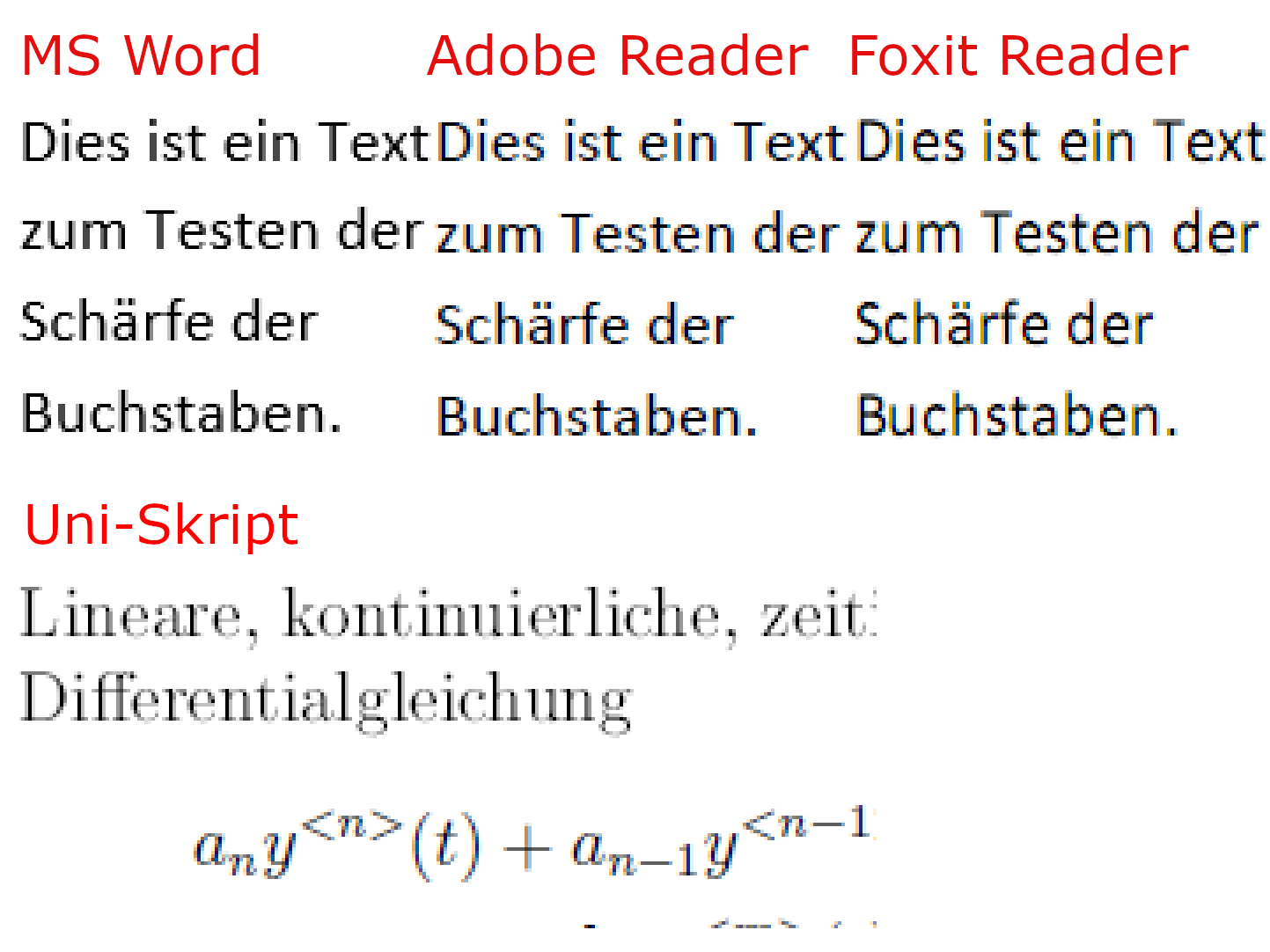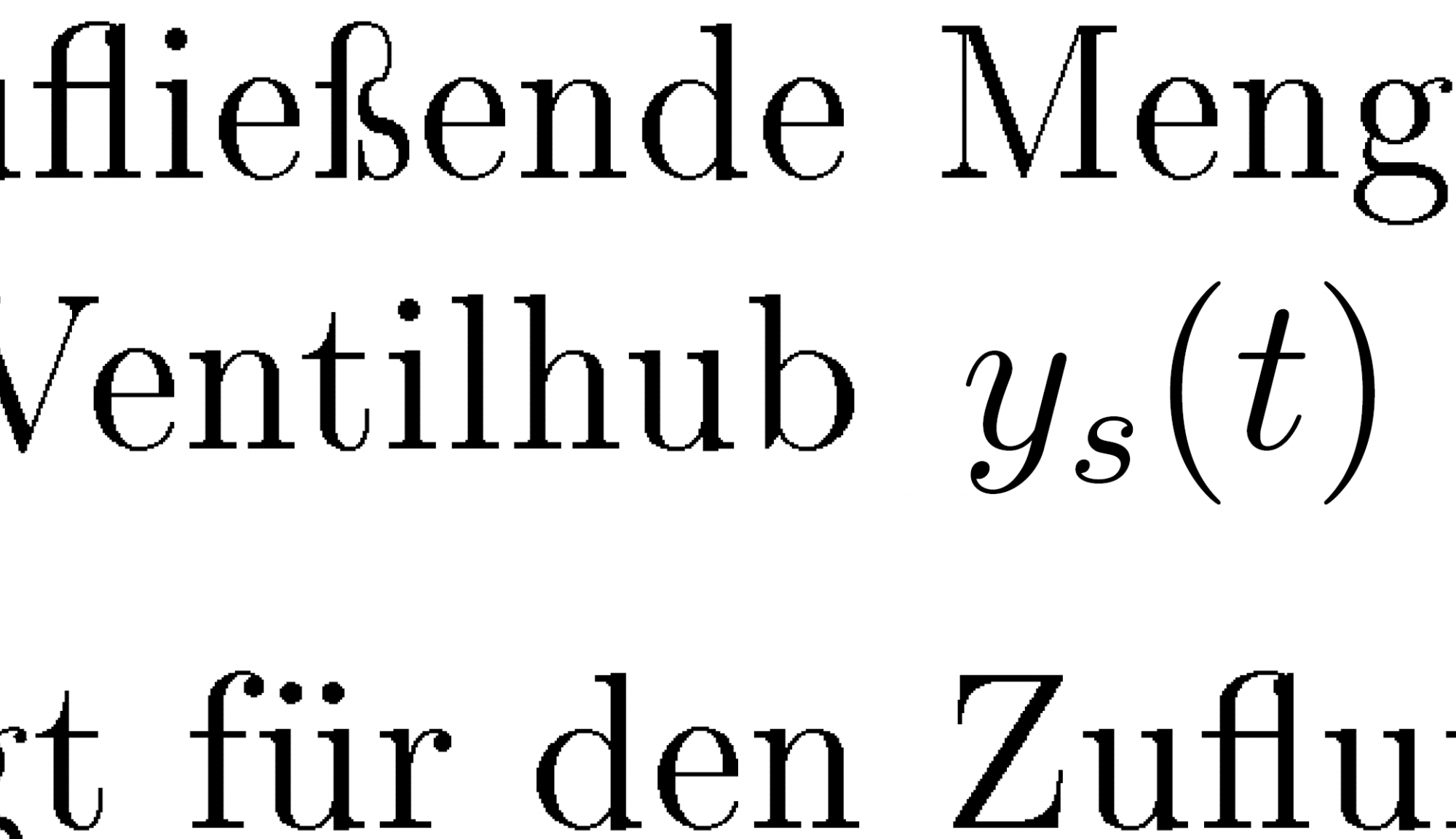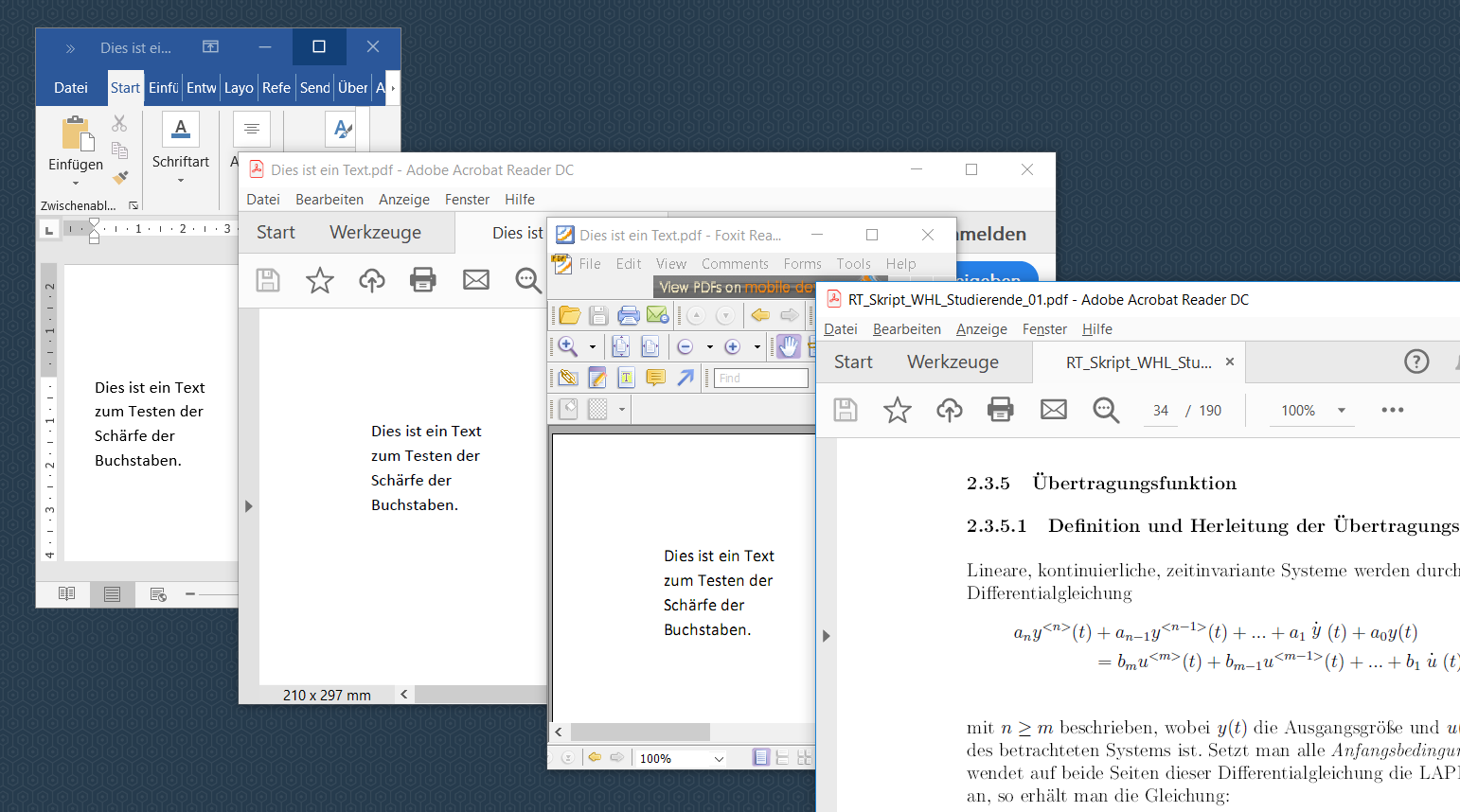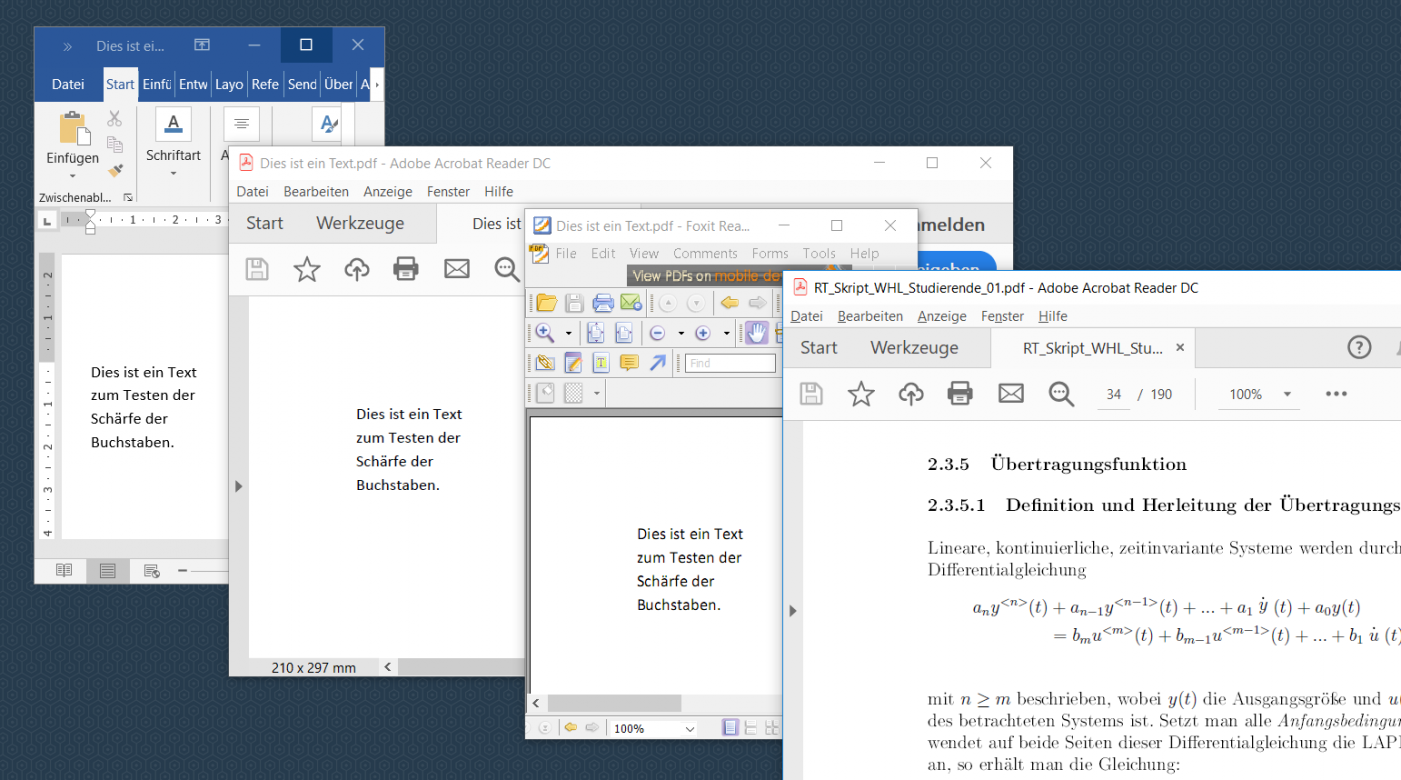
[Mitglied dyse…] Geschrieben Dezember 12, 2019 Teilen Geschrieben Dezember 12, 2019 Moin moin, mir ist das schon öfters aufgefallen. PDFs sehen immer etwas unscharf aus. Woran liegt das? Ich habe mal einen Screenshot gemacht um zu verdeutlichen was ich meine. Das ist nicht nur auf meinem PC so. Besonders fällt es mir bei Uni-Skripten die mit LaTeX geschrieben wurden auf. Vielleicht liegt das an der Schriftart, dass es da stärker ins Gewicht fällt. Bei Word ist der Text deutlich schärfer zu sehen als später in der PDF-Version des selben Dokuments. Das Skript ist nochmal deutlich unschärfer. Ich habe es auch mal vergrößert, damit man es besser sieht. Kann man das ändern? Viele Grüße Daniel Link zu diesem Kommentar
Ralf Herrmann Geschrieben Dezember 12, 2019 Teilen Geschrieben Dezember 12, 2019 Die Buchstaben sind Vektorbeschreibung. Die Umwandlung in die nötige Pixeldarstellung und die dabei angewendete Kantenglättung erfolgt durch eine Render-Engine. Software-Anwendungen können dabei auf das Betriebssystem zugreifen oder eine eigene Render-Engine mitbringen. In der Folge sehen Texte daher in verschiedenen Anwendungen oder auf verschiedenen Betriebssystemen immer etwas anders aus. Direkt eingreifen kann man da selten. (Gegebenenfalls nach Einstellungen zur Kantenglättung suchen.) Es ist auch eine Frage der Gewohnheit und Geschmacksache. Der schärfere Text ist nicht automatisch der bessere. Man kann übrigens ruhig noch näher drangehen. Dann sieht man die Unterschieden in der Kantenglättung noch besser: 2) und 3) verwenden Subpixelkantenglättung. 1) nicht. Bei 2) wird eher in der Horizontalen gearbeitet. Bei 3) auch in der Vertikalen. Kann alles seine Vor- und Nachteile haben. 1 1 Link zu diesem Kommentar
[Mitglied Call…] Geschrieben Dezember 12, 2019 Teilen Geschrieben Dezember 12, 2019 Bei LaTeX kommt es darauf an, welche Schriften eingebunden werden und auf welchem Weg das PDF erzeugt wird. Der alte, steinige Weg lautete: latex erzeugt *.dvi-Datei, dvips erzeugt Postscript-Datei, ps2pdf erzeugt PDF-Datei. Ganz zu Beginn kamen dabei sehr große, unschön aussehende PDFs heraus. Uni-Skripte sehen heute auch noch manchmal so aus. Alternativen zum umständlichen Weg: pdflatex oder xelatex 1 Link zu diesem Kommentar
[Mitglied 6701…] Geschrieben Dezember 12, 2019 Teilen Geschrieben Dezember 12, 2019 Ich würde probieren, ob ClearType daran Schuld ist, das führt ja systembedingt zu unschärferen Abbildungen. Link zu diesem Kommentar
[Mitglied Seba…] Geschrieben Dezember 12, 2019 Teilen Geschrieben Dezember 12, 2019 vor 15 Minuten schrieb bertel: Ich würde probieren, ob ClearType daran Schuld ist, das führt ja systembedingt zu unschärferen Abbildungen. Cleartype sollte eigentlich – wenn die Subpixel im Display-Panel nicht "verkehrt rum" oder gar nicht in Streifen-Anordnung positioniert sind – tendenziell schärfer, magerer, aber ein klein wenig "bunt" aussehen, da hier einzelne Farbkomponenen als Subpixel "missbraucht" werden um eine feinere Auflösung zu erhalten als eigentlich vorhanden ist (die Wahrheit am Display is deshalb auch eine andere als in den üblichen Screenshots / digitalen Zooms zum Thema zu sehen). Das ist das, was in Word unter Windows zum Einsatz kommt. Adobe hat seinen eigenen Rasterer dabei, auch damit das systemübergreifend gleich aussieht - speziell Indesign wäre sonst etwas mühsam systemübergreifend ... Dieser arbeitet nicht mit Subpixeln (Cleartype) sondern mit Graufstufen – das wirkt dann ein wenig dunkler / weicher / unschärfer. (Was hier am besten hilft: Retina / HiDPI / 4k-Displays verwenden ... echte hohe Auflösung im Display ist mit Tricks nicht zu ersetzen, und die Unterschiede verschwinden ... gerade Cleartype ist da eigentlich weitestgehend nicht mehr nötig.) Link zu diesem Kommentar
[Mitglied Tobi…] Geschrieben Dezember 12, 2019 Teilen Geschrieben Dezember 12, 2019 vor 1 Stunde schrieb Callelulli: Bei LaTeX kommt es darauf an, welche Schriften eingebunden werden und auf welchem Weg das PDF erzeugt wird. Der alte, steinige Weg lautete: latex erzeugt *.dvi-Datei, dvips erzeugt Postscript-Datei, ps2pdf erzeugt PDF-Datei. Ganz zu Beginn kamen dabei sehr große, unschön aussehende PDFs heraus. Uni-Skripte sehen heute auch noch manchmal so aus. Alternativen zum umständlichen Weg: pdflatex oder xelatex Um das zu ergänzen: ein weiteres Problem ist, das auf dem steinigen Weg u.U. nur schlecht aufgelöste Bitmap-Fonts genutzt werden, die dann naturgemäß pixelig sind. Das könntest du Prüfen, wenn du auf einen Buchstaben maximal ranzoomst. Wenn der dann aus schwarzen Quadraten zusammengesetzt ist, ist es ein Bitmap-Font, wenn aber auch die stark gezoomten Kanten ähnlich unscharf dargestellt werden, wie die ganzen Buchstaben in anderer Zoomstufe, liegt es am Rendering. 2 Link zu diesem Kommentar
[Mitglied 6701…] Geschrieben Dezember 13, 2019 Teilen Geschrieben Dezember 13, 2019 vor 8 Stunden schrieb Sebastian Nagel: Cleartype sollte eigentlich … Das war der durchaus sinnvolle Gedanke hinter Cleartype. In der Praxis haben das aber viele abgeschaltet, weil das Lesen auf Dauer zu anstrengend war. Link zu diesem Kommentar
[Mitglied dyse…] Geschrieben Dezember 13, 2019 Themen-Ersteller Teilen Geschrieben Dezember 13, 2019 Danke für eure Antworten! Vielleicht hätte ich zu meinem Monitor noch etwas schreiben sollen. Das habe ich nicht getan, weil es mir wie gesagt auf anderen Arbeitsplätzen auch auffällt. Meinen Monitor habe ich gerade ein paar Wochen lang (Samsung LU32J590UQUXZG). Der hat 3840 x 2160 Auflösung bei 32" Diagonale. Der alte HD4000 Grafikkern meines Laptops schafft aber leider nur 2560 x 1440, weshalb ich bis auf weiteres auf die volle Auflösung verzichten muss. Umso wichtiger wäre mir ein scharfes Rendering durch die Software, damit nicht zwei Unschärfefaktoren zusammen kommen. Es ist aber auch akzeptabel, nur eben etwas suboptimal, weshalb ich hier mal die Experten fragen wollte ob man da irgendwas einstellen kann oder jemand eine andere Software kennt, die insbesondere PDFs schärfer rendern kann. Das Skript benutzt tatsächlich einen Bitmapfont für den Text. Für Formeln sind es gerenderte Fonts. Im Screenshot unten sieht man eine Stelle mit beiden Varianten ( ys(t) ist deutlich schärfer ). Ich vermute, dass auch die Fontgestaltung mit seinen Schnörkeln und dicken und dünnen Stellen die Darstellung schwierig macht. Mit ClearType habe ich schon herumgespielt, da konnte ich keine Besserung erzielen. Ich habe es aber aktiviert gelassen, weil mir die Darstellung minimal besser erscheint (das ist aber an der Wahrnehmungsgrenze). 1 Link zu diesem Kommentar
[Mitglied Klau…] Geschrieben Dezember 13, 2019 Teilen Geschrieben Dezember 13, 2019 Was ist mit der Textdarstellung bei Vergrößerung und/oder Ausdruck? Wenn die Schriftkanten dann immer noch unscharf sind, besteht das Problem bei der Erstellung. Mir fällt immer auf, das feine Linien in einer PDF-Datei auf dem Bildschirm immer fetter erscheinen, als sie sein sollten. Wenn ich in das Dokument »reinzoome« werden sie richtig dargestellt. Deshalb achte ich bei der Erstellung von Formularen, die am Bildschirm ausgefüllt werden sollen, immer darauf, nicht allzufeine Linien zu verwenden. Beste Grüße Link zu diesem Kommentar
[Mitglied dyse…] Geschrieben Dezember 13, 2019 Themen-Ersteller Teilen Geschrieben Dezember 13, 2019 Bei Ausdruck ist alles sehr scharf. Link zu diesem Kommentar
[Mitglied Tobi…] Geschrieben Dezember 13, 2019 Teilen Geschrieben Dezember 13, 2019 vor 33 Minuten schrieb KlausWehling: Wenn die Schriftkanten dann immer noch unscharf sind, besteht das Problem bei der Erstellung. Im gezeigten TeX-Beispiel ist das Problem tatsächlich die Erstellung, da kann man dann als Leser nix machen, außer den Autor freundlich drauf hinweisen, dass er mal sein TeX-System aktualisiert und „moderne“ Schriften nutzt. Siehe bspw. https://tex.stackexchange.com/q/1291/4918 Link zu diesem Kommentar
[Mitglied dyse…] Geschrieben Dezember 14, 2019 Themen-Ersteller Teilen Geschrieben Dezember 14, 2019 Hahaha, das ist lustig. Es ist genau der Prof., der uns zwingen will für Laborberichte TeX zu verwenden und dann aber zugeben musste, dass er das rechtlich nicht kann. Ihn soll ich jetzt darauf hinweisen, dass sein TeX-System verbesserungswürdig ist? Da lasse ich besser die Finger von. Es scheint schon Kränkung genug zu sein, dass wir uns seinem dringenden Wunsch widersetzt haben. Einige TeX-Fans sind wirklich fürchterlich überzeugt von ihrer Meinung und denken es ginge nur so und nicht anders. Link zu diesem Kommentar
[Mitglied Call…] Geschrieben Dezember 15, 2019 Teilen Geschrieben Dezember 15, 2019 vor 20 Stunden schrieb dysentrieb: Es scheint schon Kränkung genug zu sein, dass wir uns seinem dringenden Wunsch widersetzt haben. Einige TeX-Fans sind wirklich fürchterlich überzeugt von ihrer Meinung und denken es ginge nur so und nicht anders. Bestimmt gibt es auf jeder Seite die Ideologen, die die Nichtnutzung ihres geliebten Programmes als Sakrileg betrachten. Daneben kann es aber auch gute, sachliche Gründe geben, weshalb Dein Professor seinen Studenten LaTeX nahelegt. Bei mir in der Arbeit würde ich gerne LaTeX einsetzen. Ich habe sämtliche Pro-Argumente gesammelt und kann nahezu alle Contra-Argumente beantworten. Die Gegenseite hat aber ebenso gute Argumente. Ich akzeptiere, daß derjenige, der die Verantwortung trägt, anders entscheidet. Ob Du Dir einen Gefallen tust, Dich seinem Wunsch zu widersetzen? Link zu diesem Kommentar